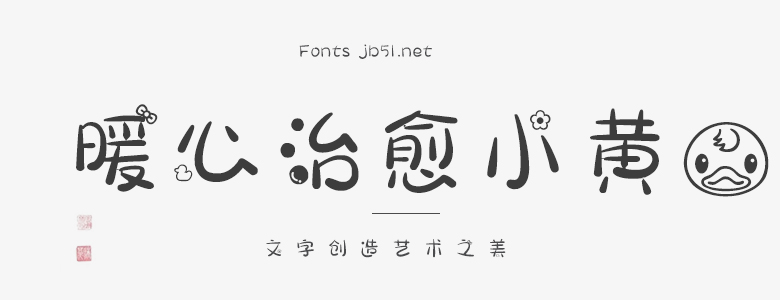
暖心治愈小黃鴨是一款專為閱讀體驗設計的字體,其風格清新、柔和,充滿了溫暖和親切感。這款字體的筆畫設計巧妙地融合了小黃鴨的形象特征,使其既具有字體的實用性,又不失趣味性和可愛感。 暖心治愈小黃鴨的字母形狀以圓潤為主,給人一種柔和、舒適的感覺。其筆畫細節(jié)處理得非常精細,保證了字體的清晰度和易讀性。此外,字體家族還包括一些特殊字母和符號,如“ü”、“é”等,豐富了文字的表達方式,為使用者提供了更多的可能性。 總體來說,暖心治愈小黃鴨字體設計獨特,富有創(chuàng)意,不僅適合用于兒童和教育領域的文本呈現(xiàn),還適用于溫暖、治愈系的主題內容,能夠帶給讀者溫馨、舒適的閱讀體驗。